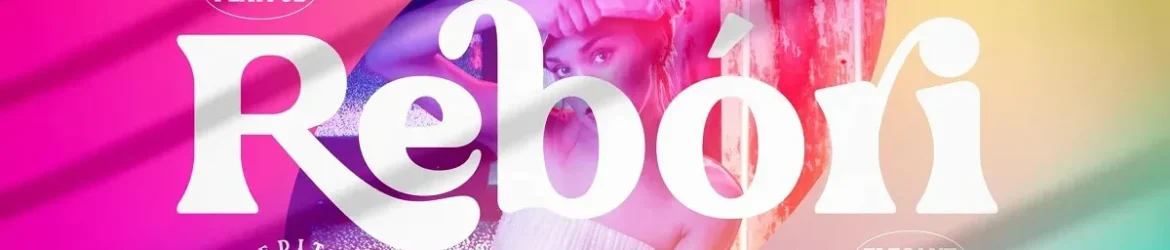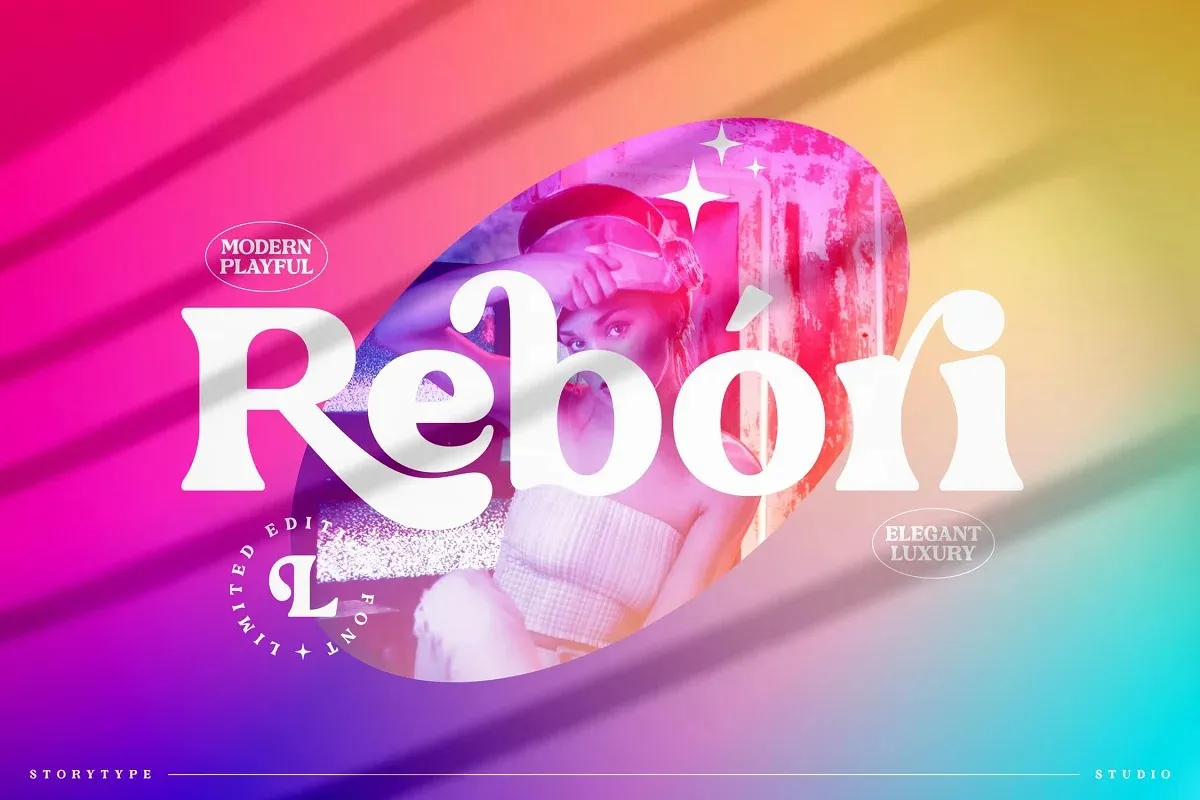
Rebori Serif Font – Fonte Grátis
Rebori Serif Font
A fonte Rebori Serif oferece uma experiência visual elegante e sofisticada para qualquer projeto onde você deseje incorporar estilo e requinte. Esta fonte bold moderna é repleta de detalhes que a tornam perfeita tanto para o design de logomarks, títulos de livros ou filmes quanto para marcas de moda, revistas, etiquetas, frases curtas e muito mais. As suas linhas serifadas proporcionam um ar elegante e sofisticado, ideal para quem busca uma fonte que transmite elegância e sofisticação em seus projetos visuais. A Rebori Serif é um recurso indispensável para designers gráficos atentos aos detalhes, buscando transmitir status e qualidade em suas criações. Sempre atualizada com novas versões e alternativas de design, a Rebori Serif continua a ser uma escolha confiável para qualquer projeto que você desejasse dar um toque requintado e sofisticado.